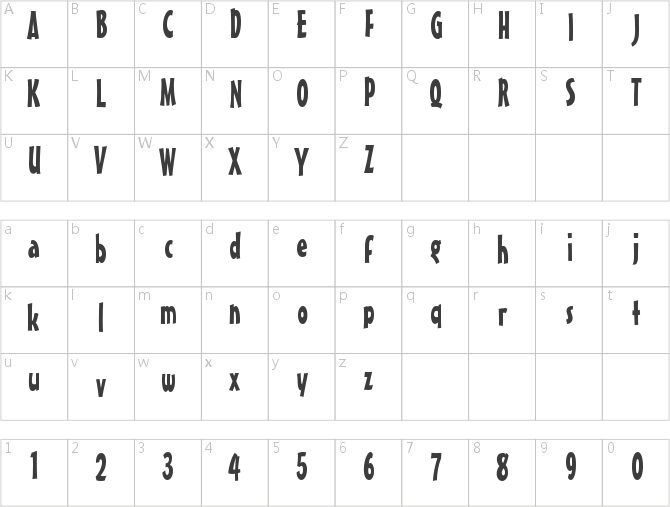
Massey-Condensed-Normal 詳情頁
Massey-Condensed-Normal字體字庫是一款讓人賞心悅目、百看不厭的英文字體,適合各類廣告和產(chǎn)品包裝設(shè)計(jì)應(yīng)用,字體大小0.04MB,格式為ttf字體,上傳用戶是高塔。,作者/版權(quán)方為未知